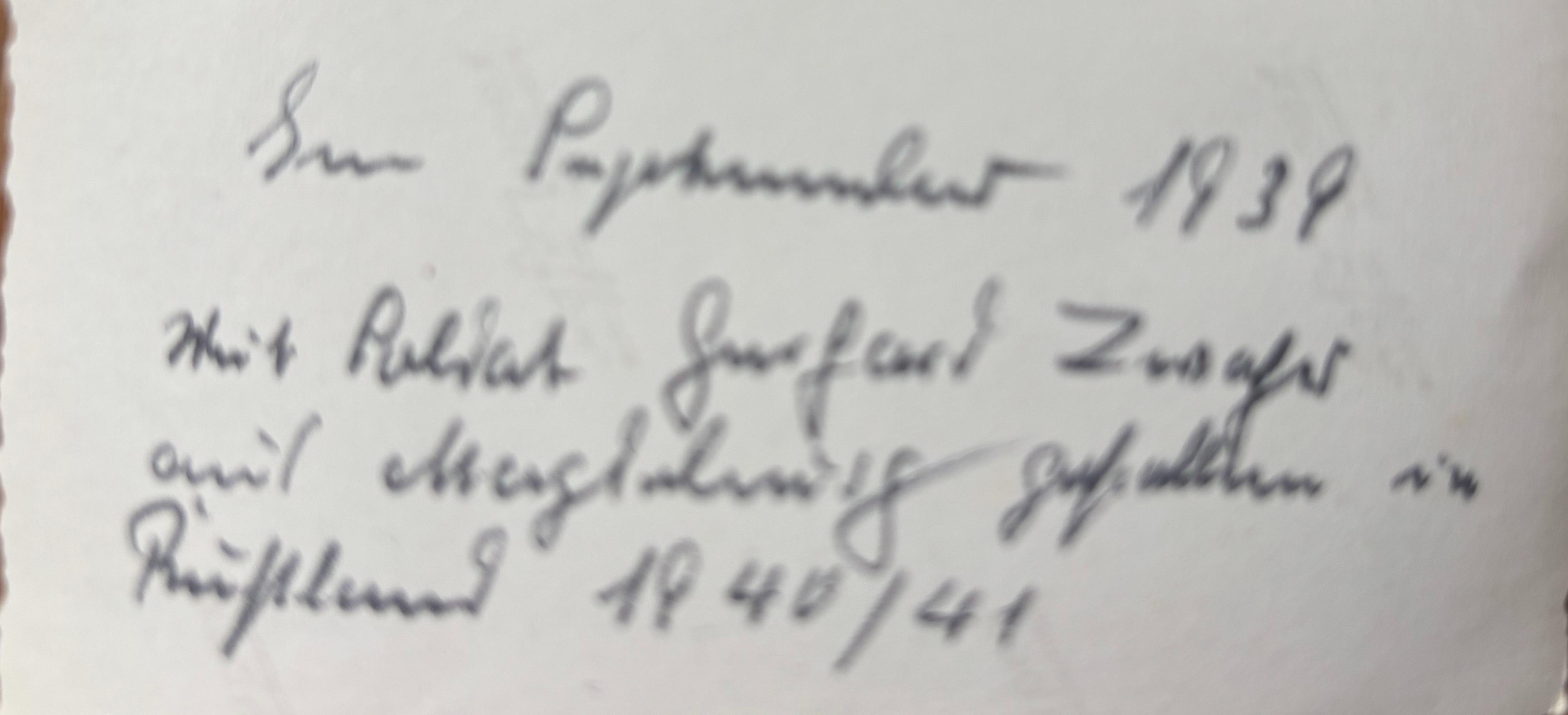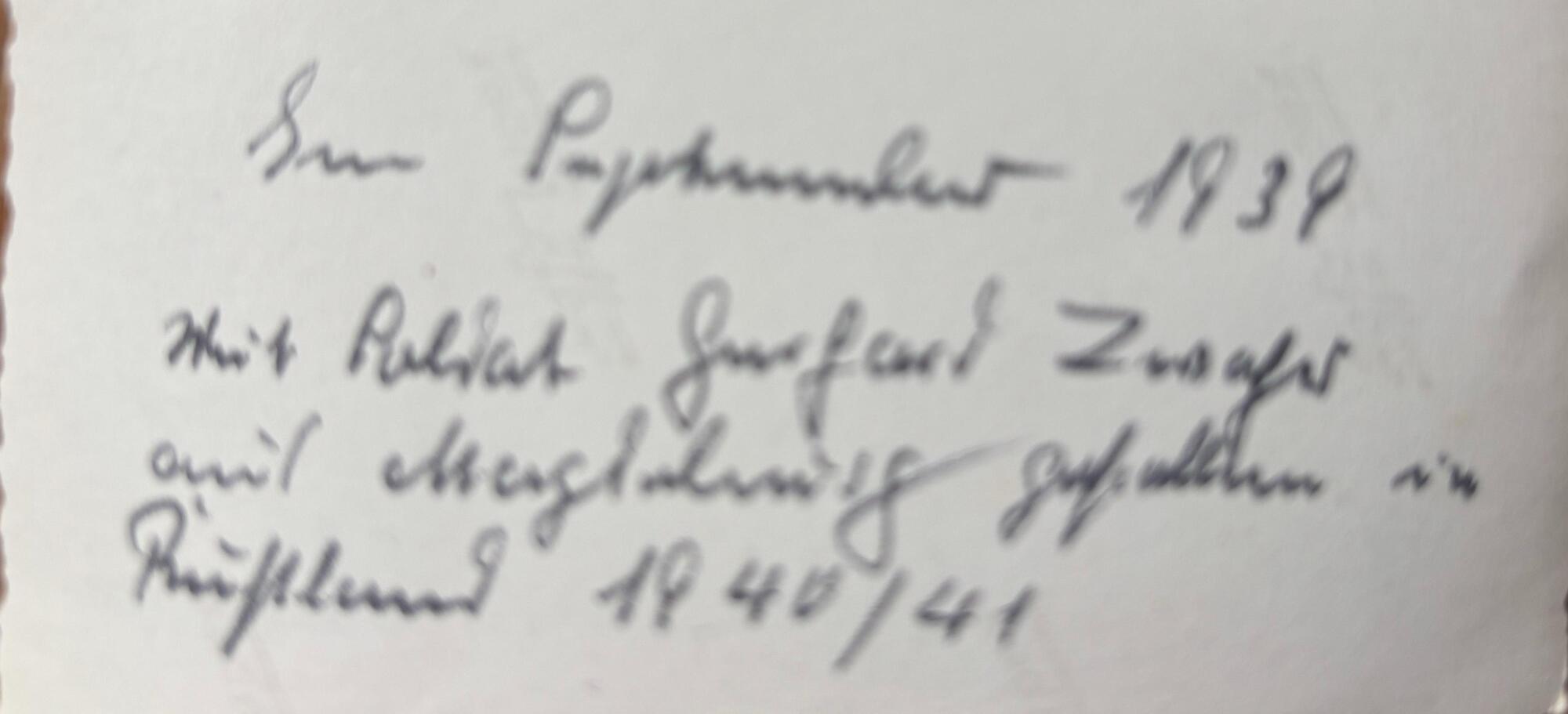
Fotounterschrift Nachname unleserlich - Bitte um Hilfe
den folgenden Text kann ich entziffern, nur den Nachnamen ("... Soldat Gerhard ???? aus Magedeburg gefallen ...") leider nicht. Vielleicht kann mir jemand helfen?
Also ohne mich groß auszukennen würde ich dort »Zwager« lesen. Und »Gerhart« eher mit »t«.
eher mit »t«
Eher nicht, der letzte Buchstabe ist eindeutig ein »d«, wie auch der Vergleich mit dem Schluss-t des vorhergehenden Worts zeigt.
»Zwaher« scheint mir wahrscheinlicher. Das »h« entspricht dem in Gerhard und das g schreibt er mit offenem Kringel oben, siehe Magdeburg.